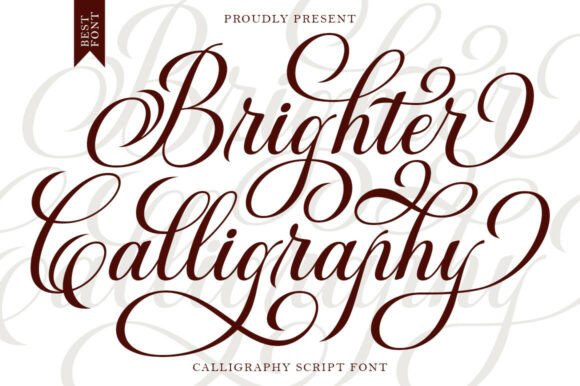
Brighter Calligraphy
Jeśli szukasz wysokiej jakości materiałów, takich jak Brighter Calligraphy, ten pakiet premium to fantastyczny wybór dla Twoich kreatywnych projektów.
Niezależnie od tego, czy tworzysz produkty POD (druk na żądanie), zaproszenia ślubne czy grafiki do mediów społecznościowych, Brighter Calligraphy będzie idealnym wyborem.